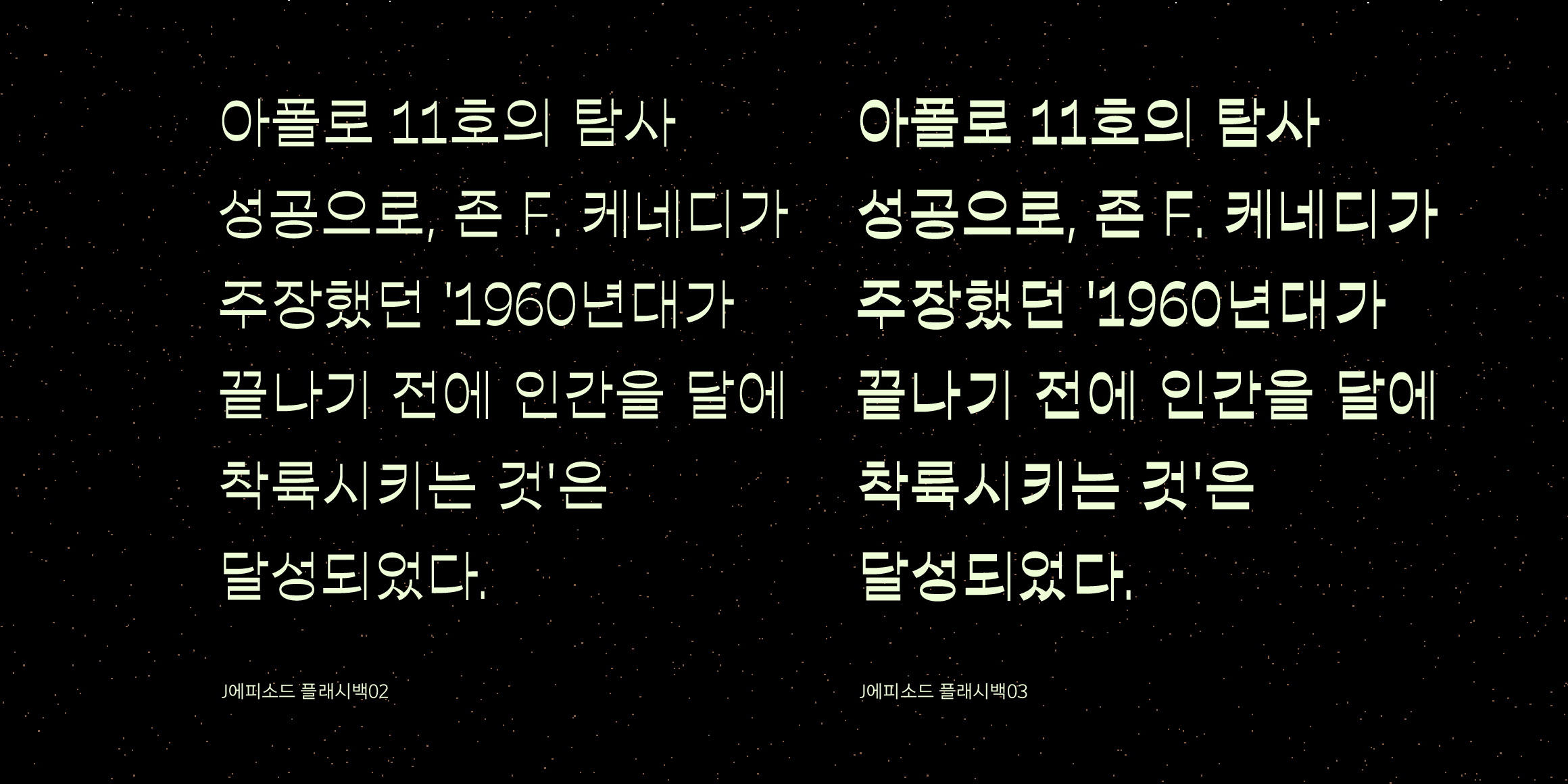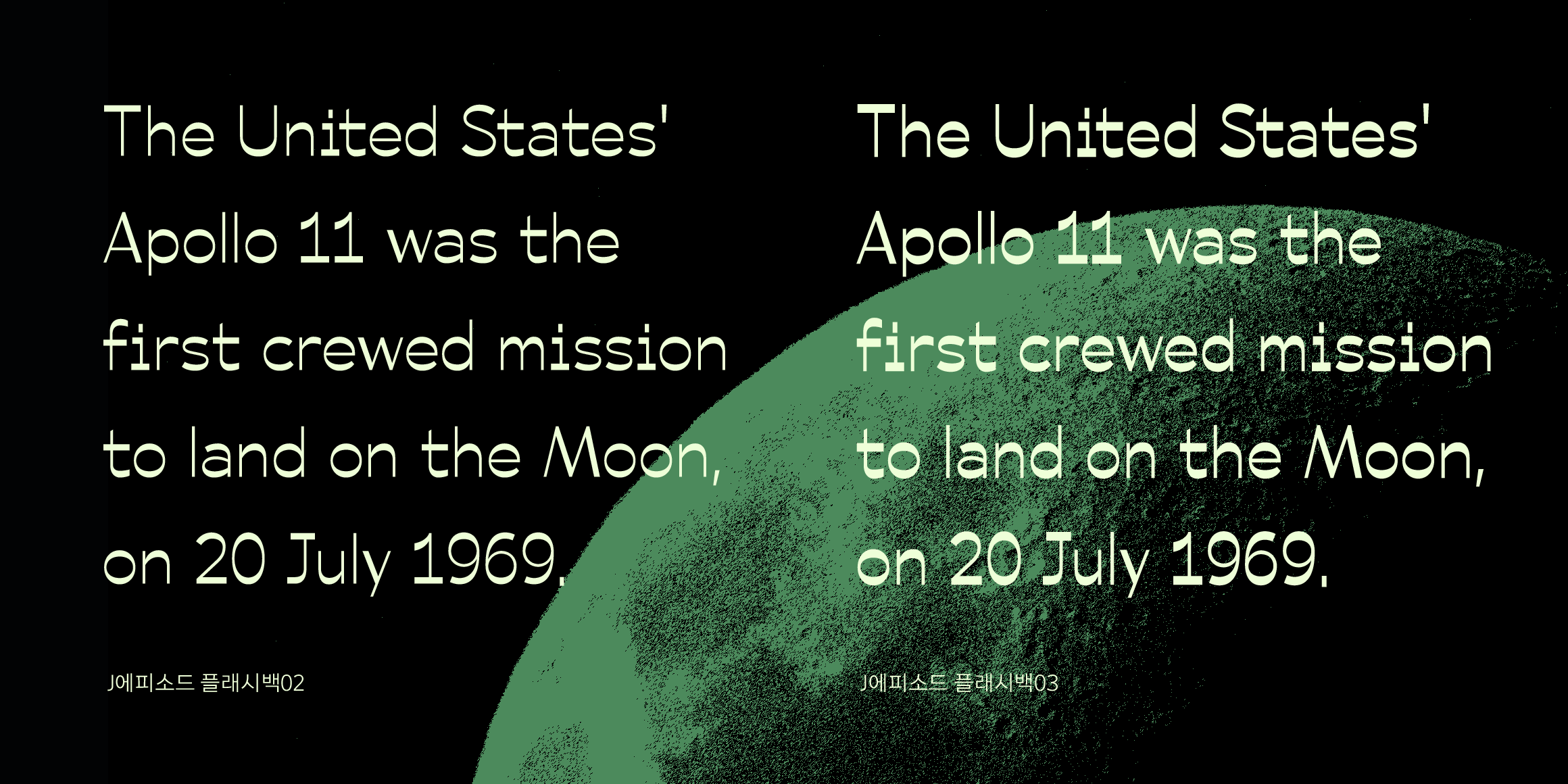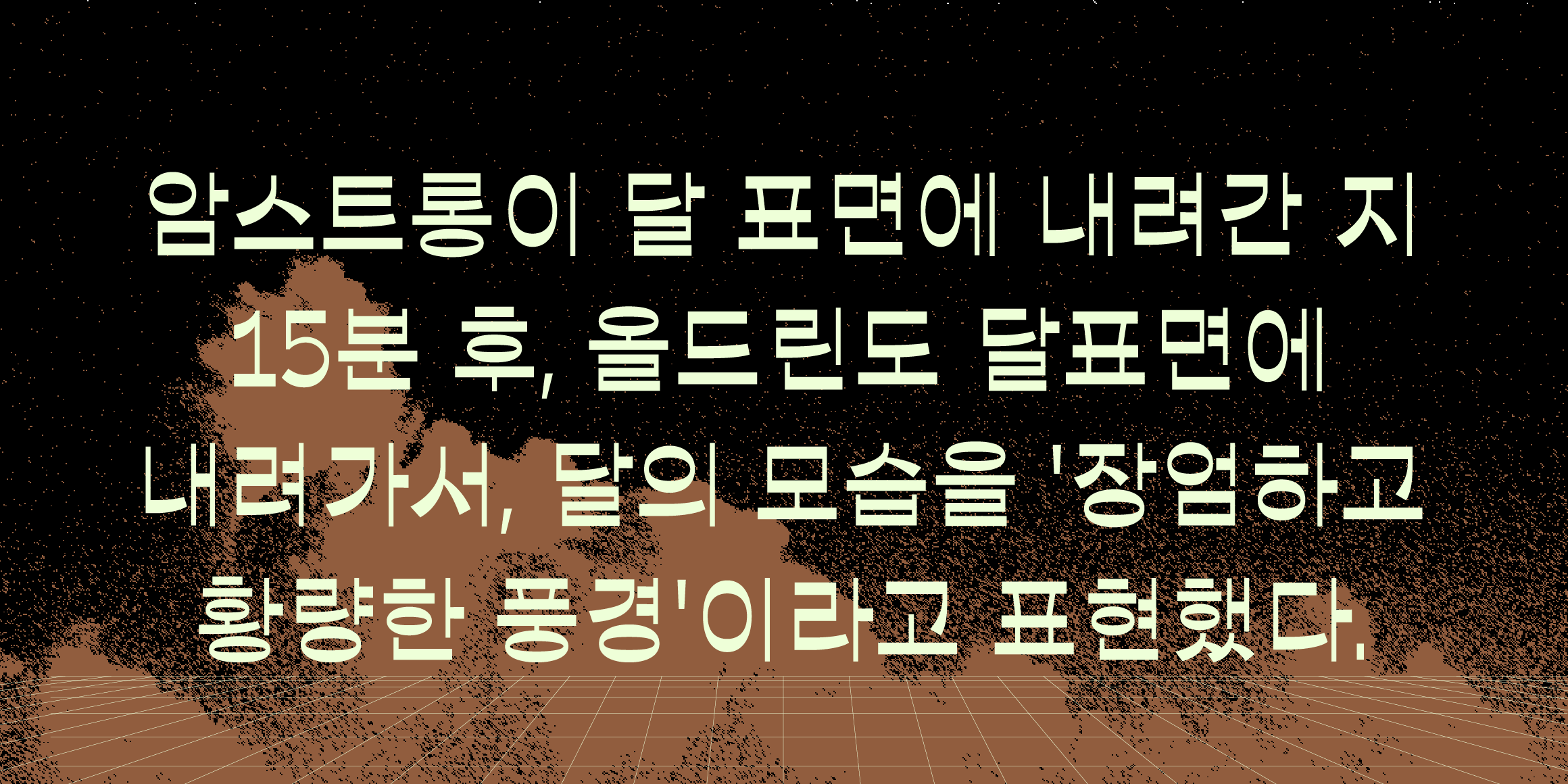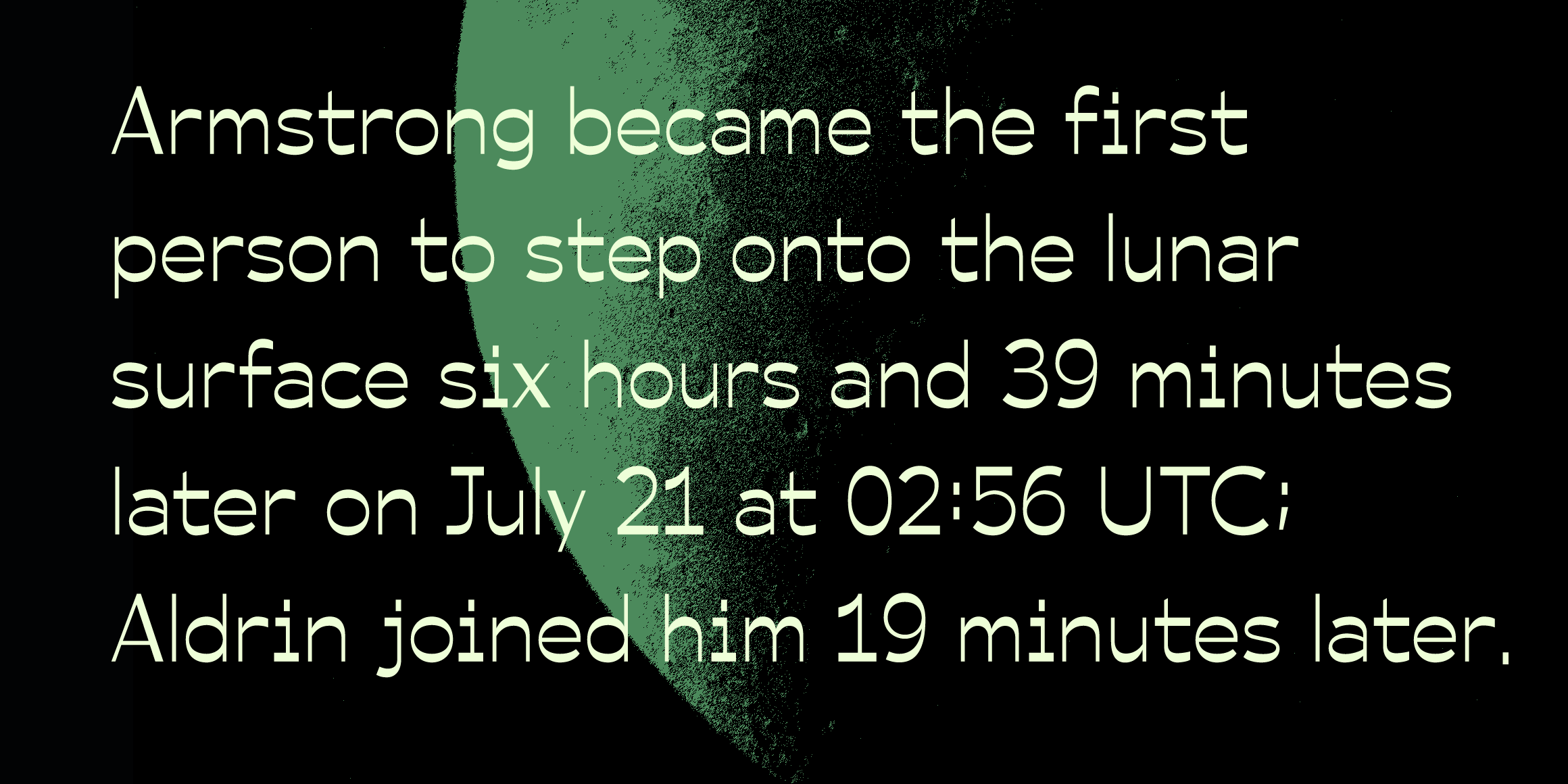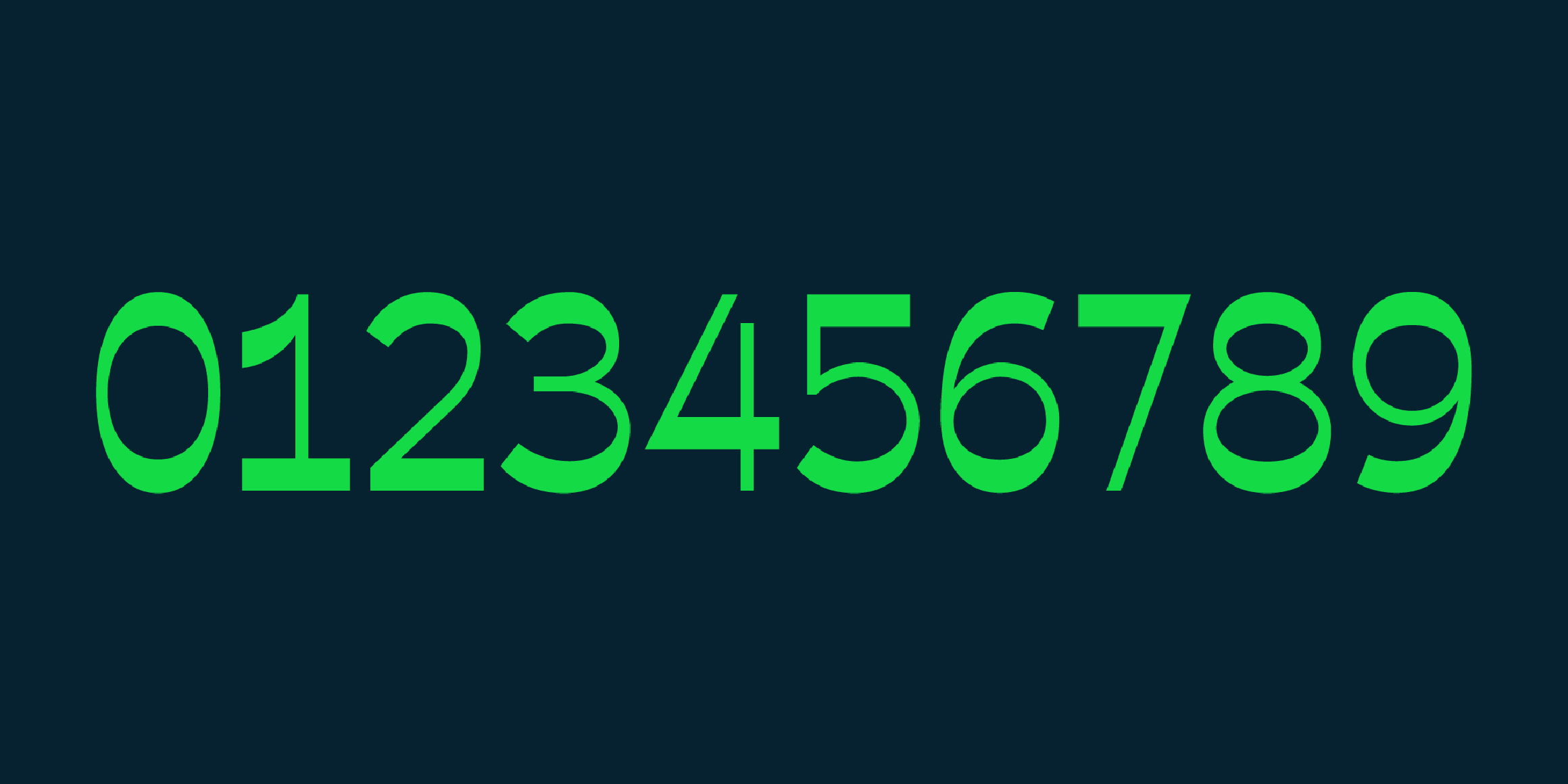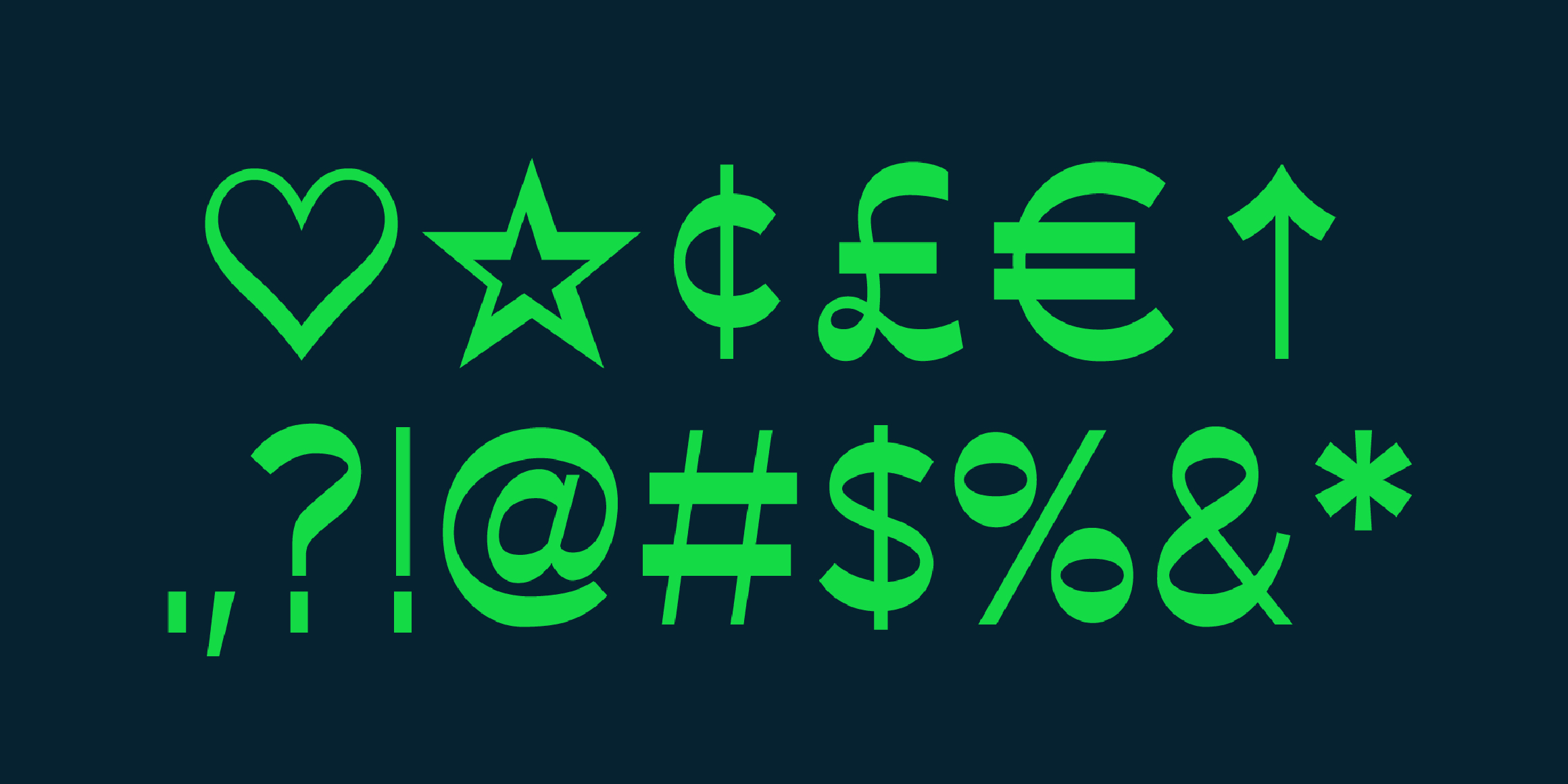
에피소드_플래시백은 J에피소드의 가로와 세로 획 두께 반전으로 기획했으며 새로운 패밀리의 확장을 보여줍니다.J에피소드의 패밀리를 이어가기 위해 글자 안에서 적절한 곡선과 직선의 분배를 보여주지만 획 대비의 반전을 통해 상반된 인상을 보여줍니다.
‘과거와 맞닿은 미래’ 폰트를 지향하며 최정호 선생의 공작체를 모티브로 참고했습니다. 레트로의 감성은 가져가되 지금 시대에서 필요로 하는 폰트에 대한 고민을 더하여 출시한 서체입니다.